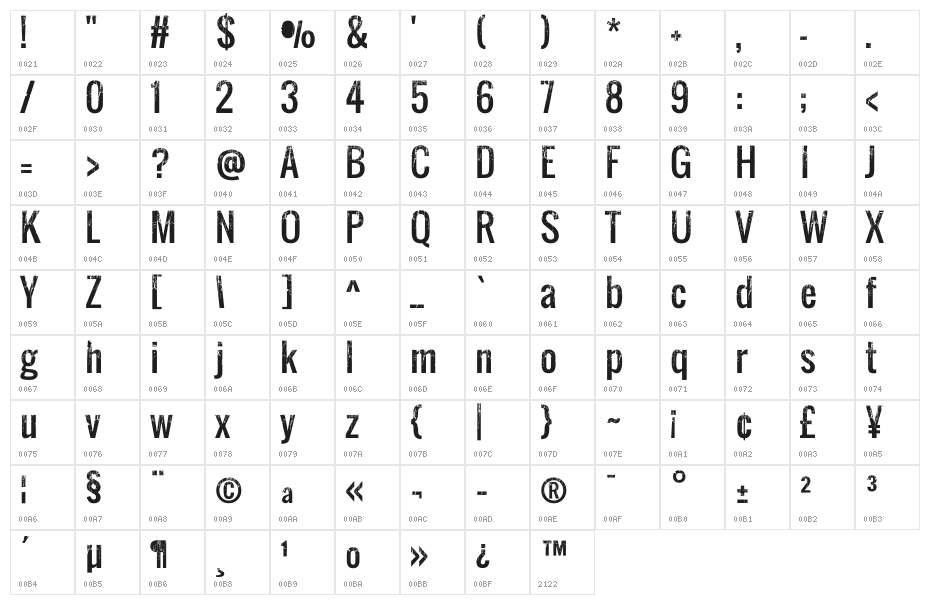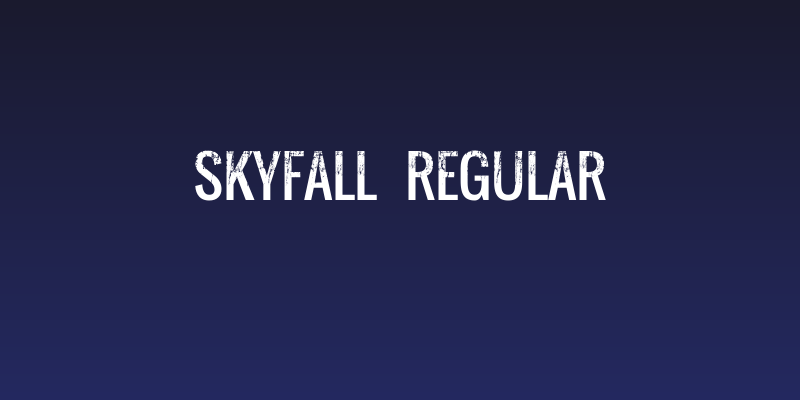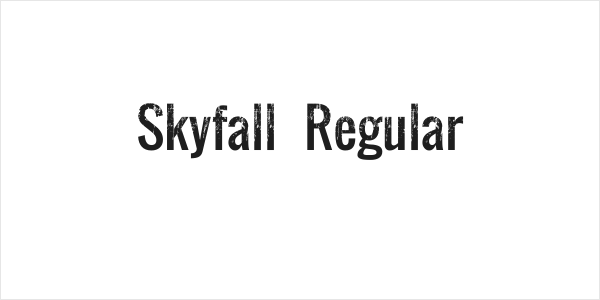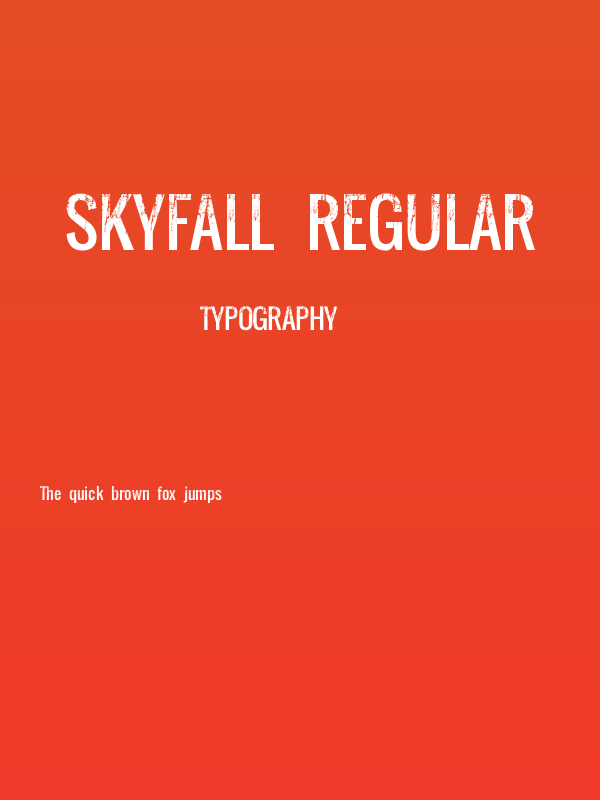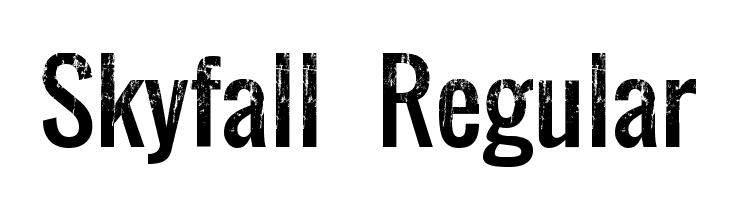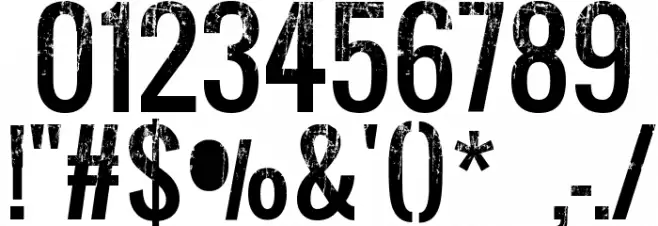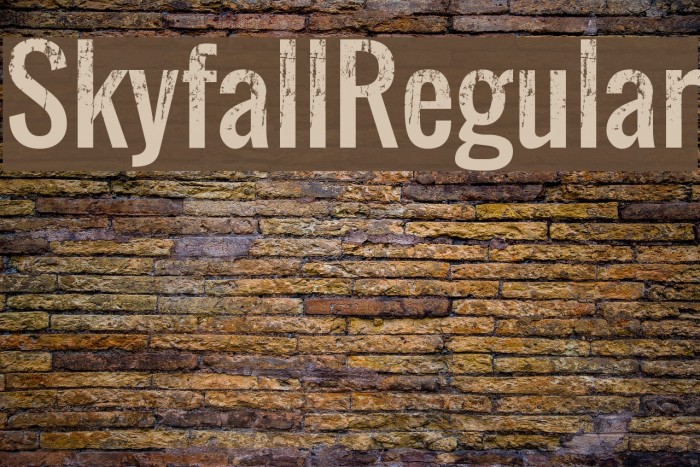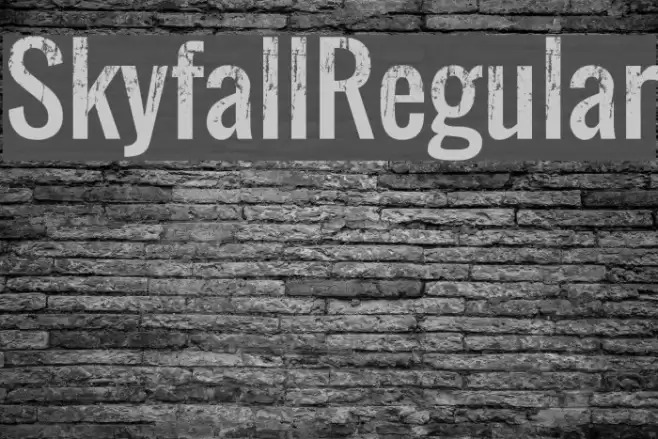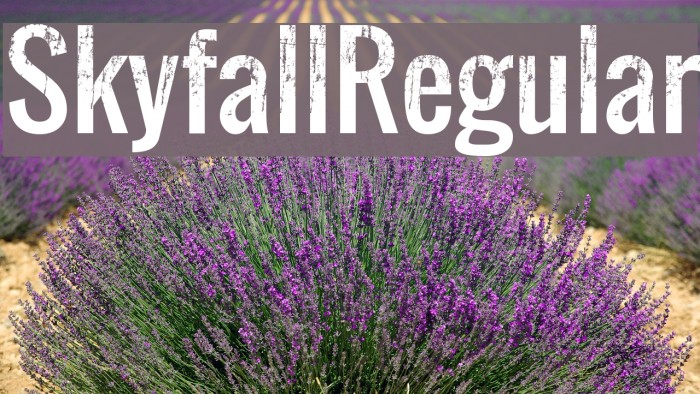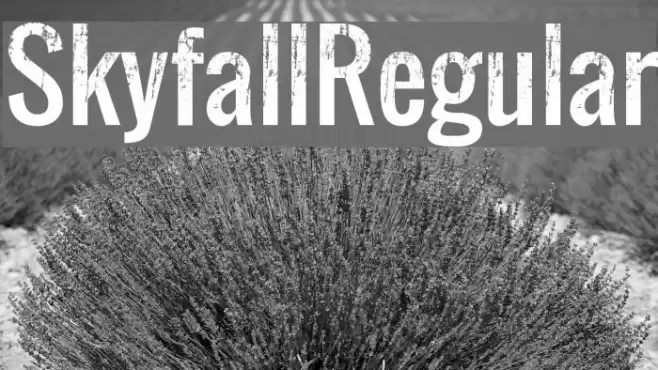
Skyfall Regular Font
✎ Distorted Eroded
| おすすめプロジェクト | Ideal for vintage-themed posters, album covers, branding for rustic products, or any design needing a strong, nostalgic impact. |